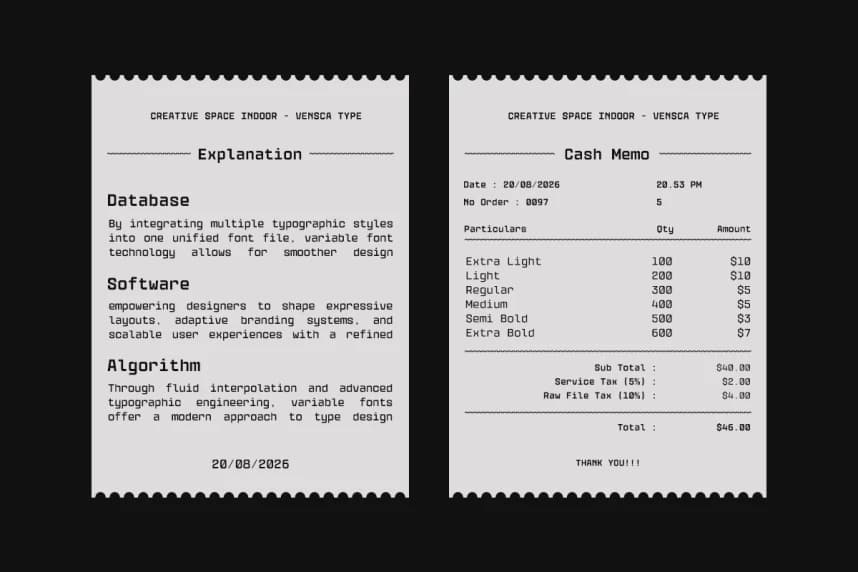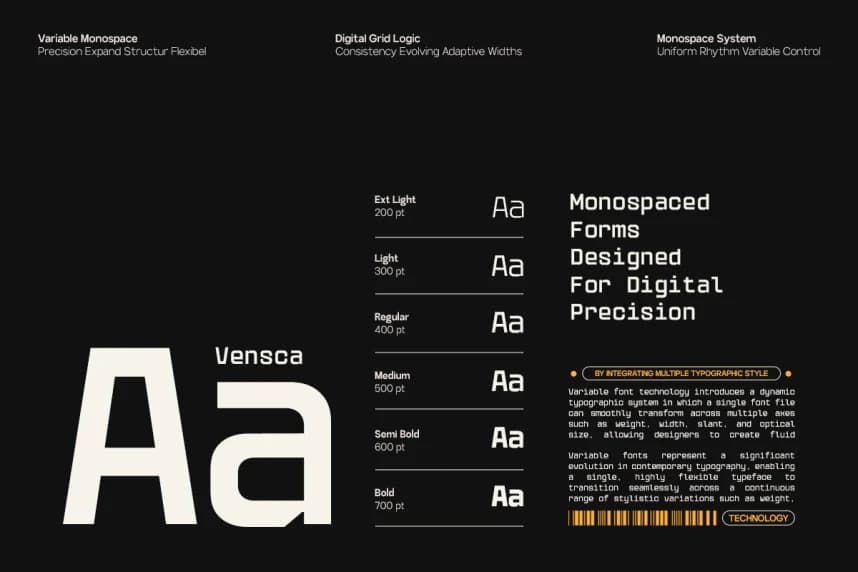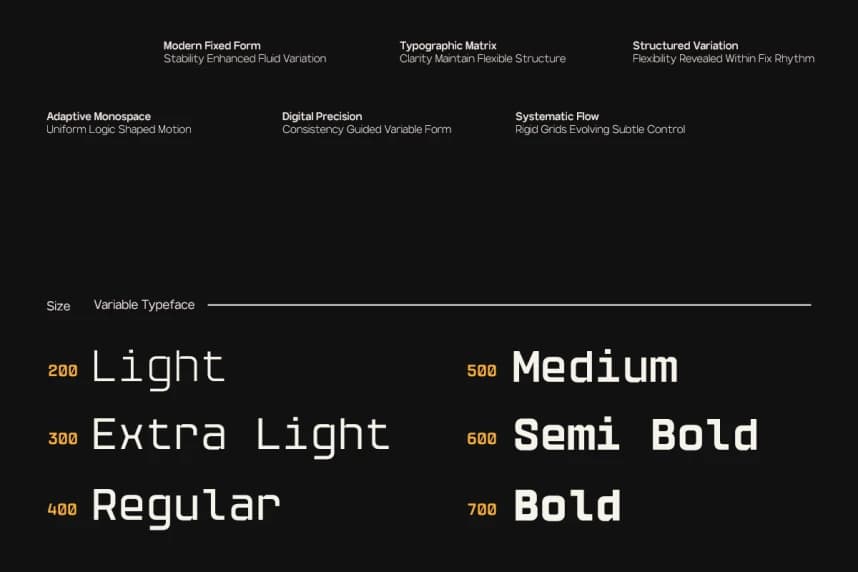
GC Vensca Mono Font
GC Vensca Mono Font – Modern Monospace, temiz yapı ve modern hassasiyetle tasarlanmış çağdaş bir monospace yazı tipidir. Tutarlı bir ızgara sistemi üzerinde kurulu ve ince ayarlı oranlara sahip olan Vensca Mono, modern görsel iletişim için uygun, net, teknik ve kendinden emin bir tipografik üslup su
GC Vensca Mono Font – Modern Monospace, çağdaş bir sabit genişlikli yazı tipidir ve temiz bir yapı ile modern hassasiyetle tasarlanmıştır. Tutarlı bir ızgara sistemi üzerinde ve rafine oranlarla, Vensca Mono net, teknik ve kendinden emin bir tipografik üslup sunar; modern görsel iletişim için uygundur.